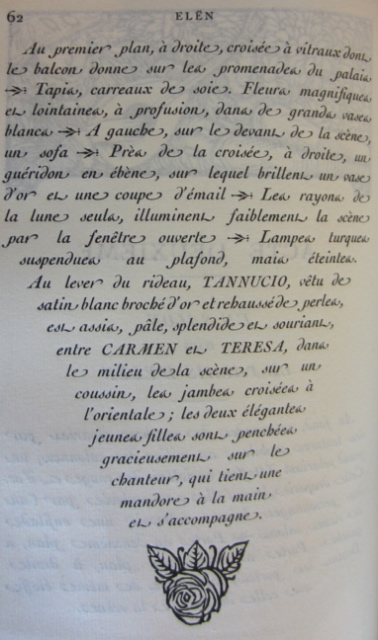
Subject: | [typo] Quel est donc ce caractère ? |
Tout est dans le titre, sauf l'image qui est ci-dessous.Une précision : il s'agit d'une page d' Elën, de Villiers d'Adam, édité par Crès en 1918. La vignette en bois du cul de lampe est de Jou (mais pas les caractères puisque le premier livre imprimé avec ses propres caractères étant le Prince de Machiavel en 1921).